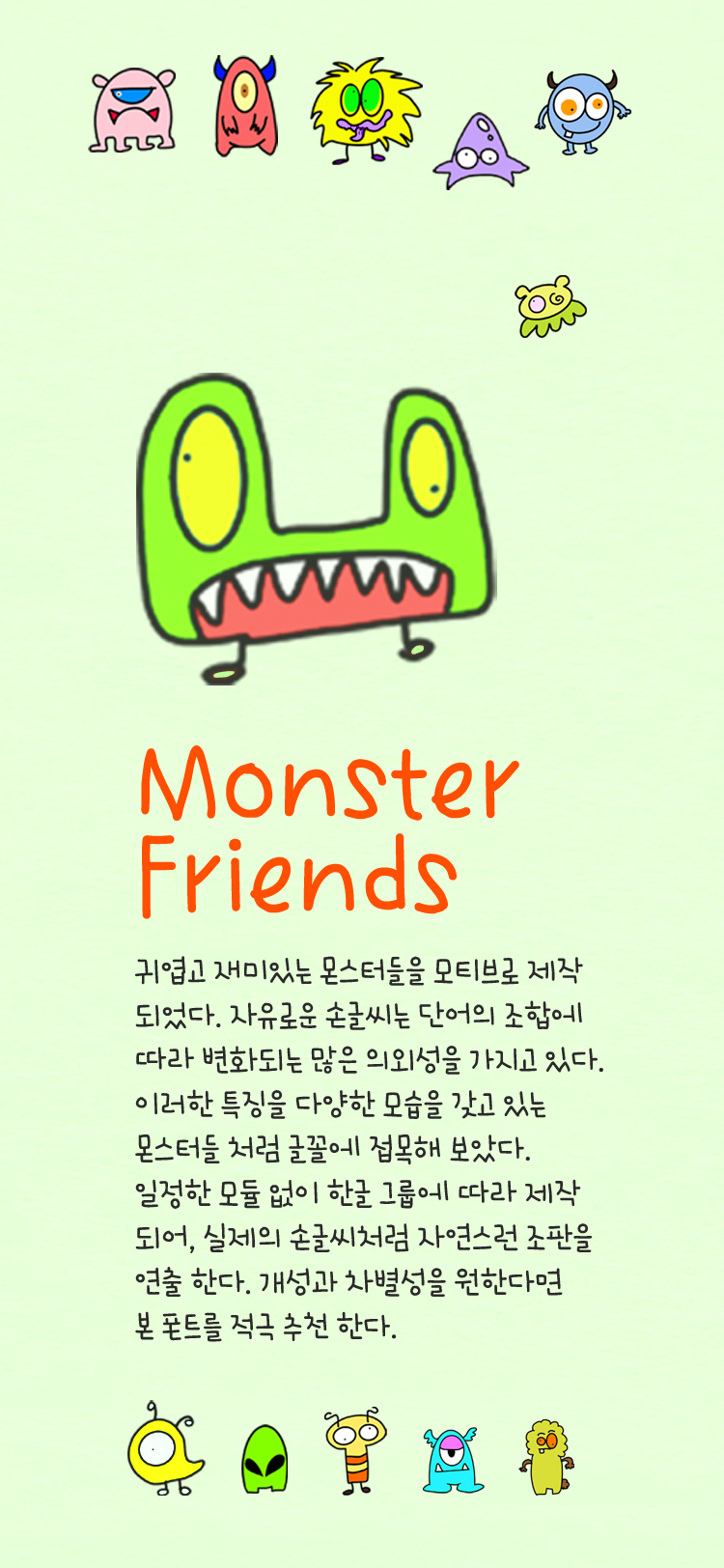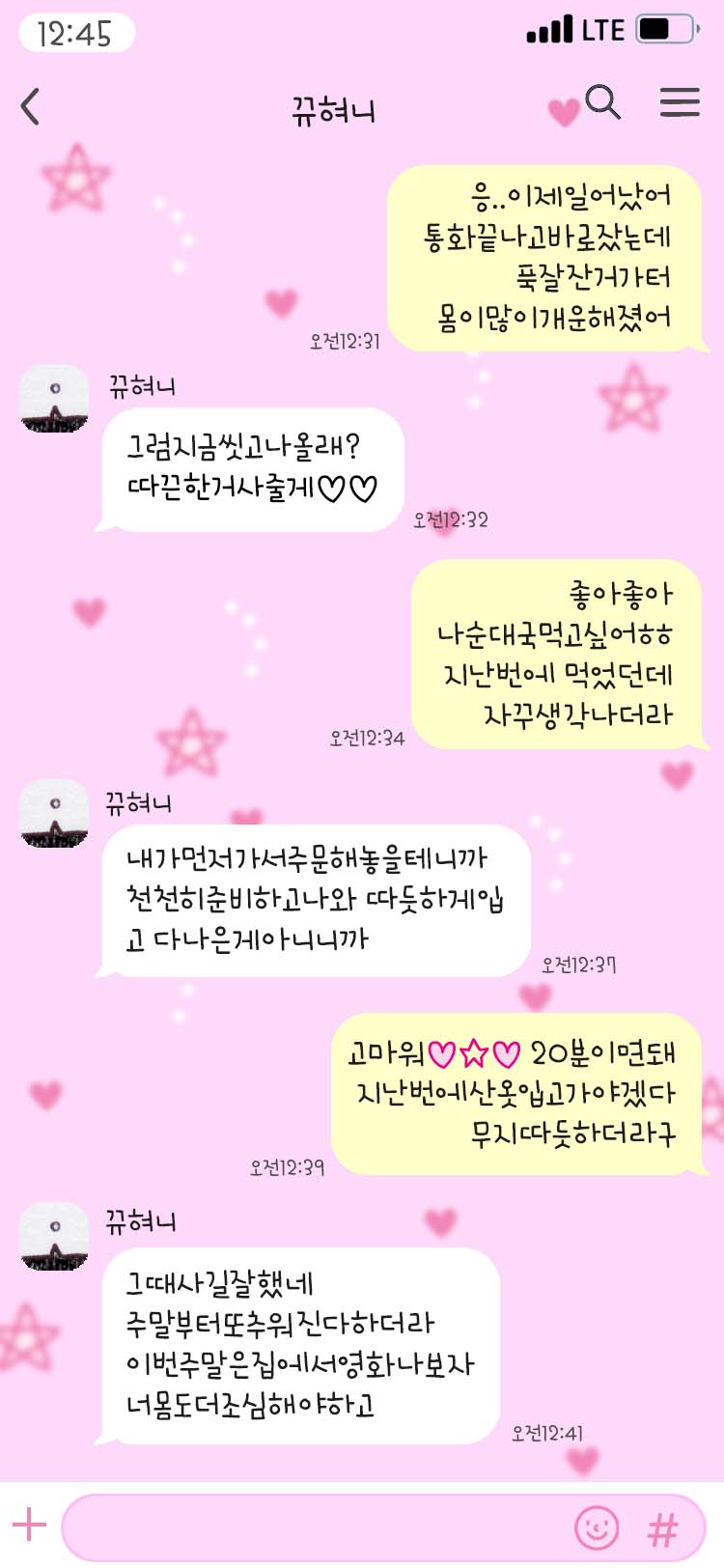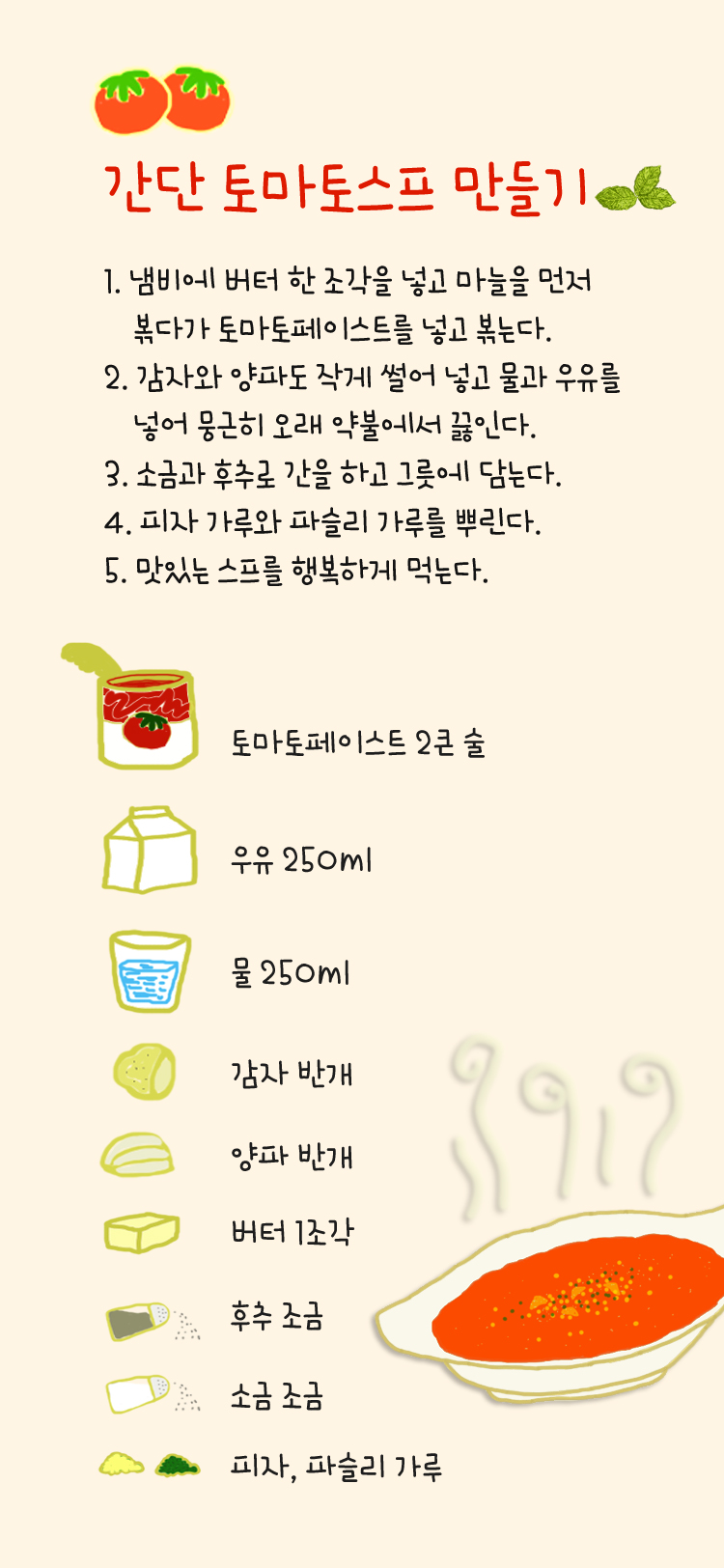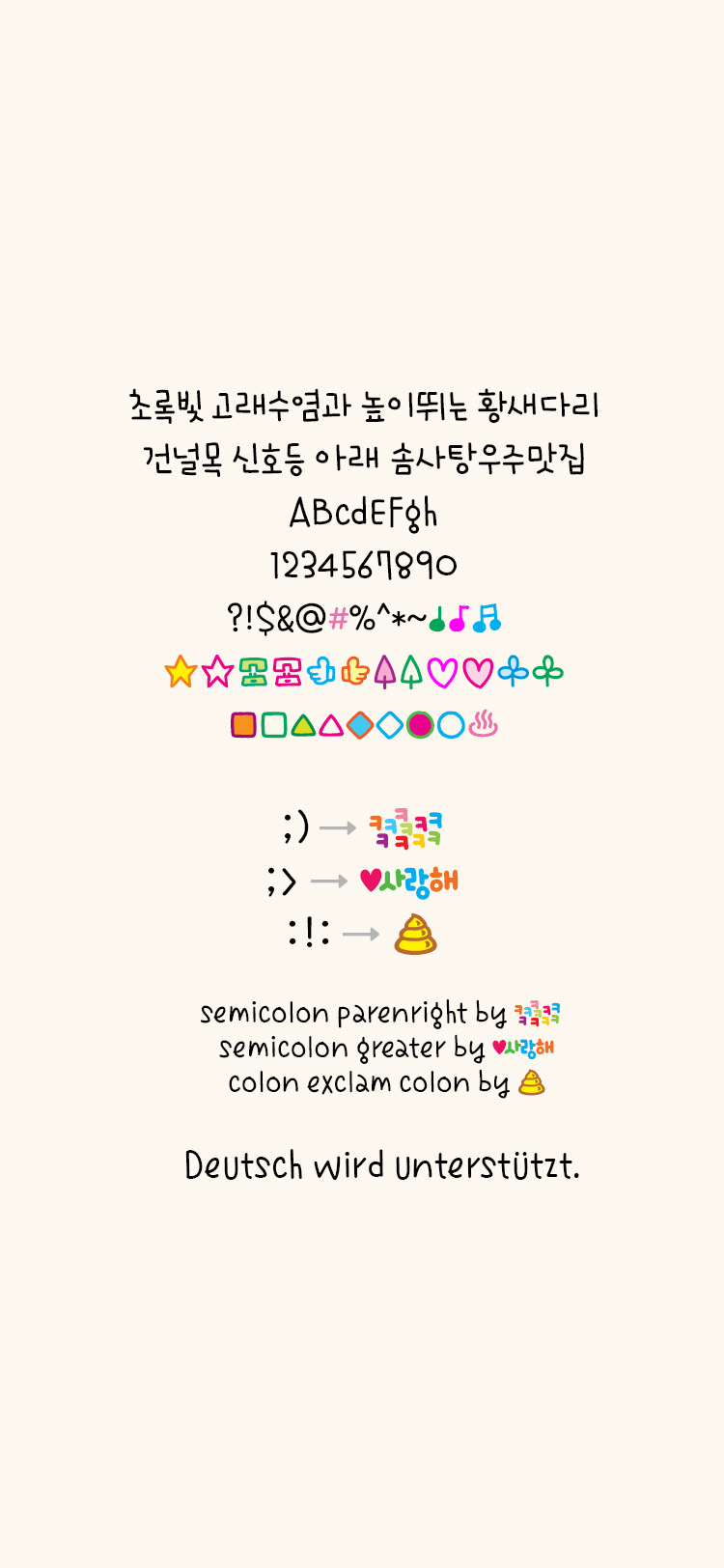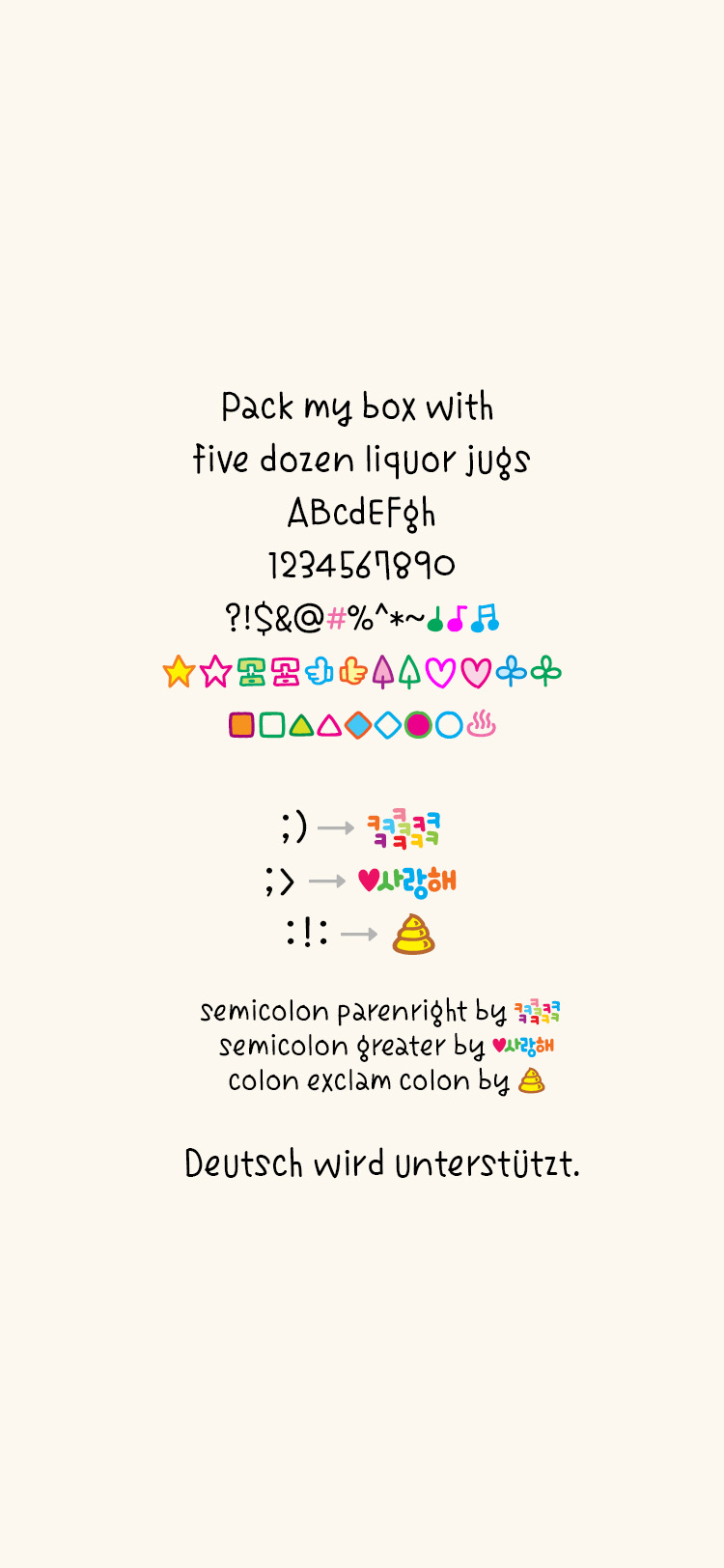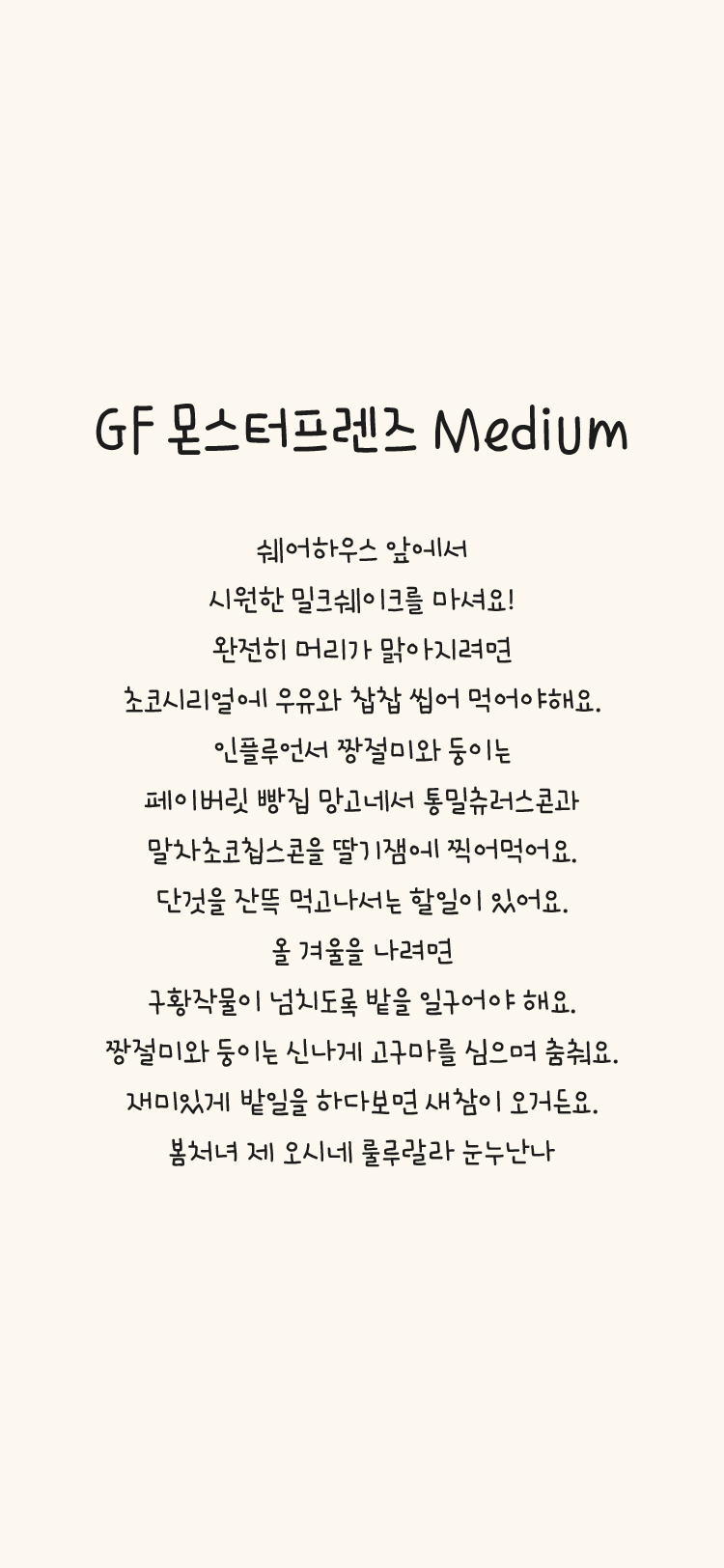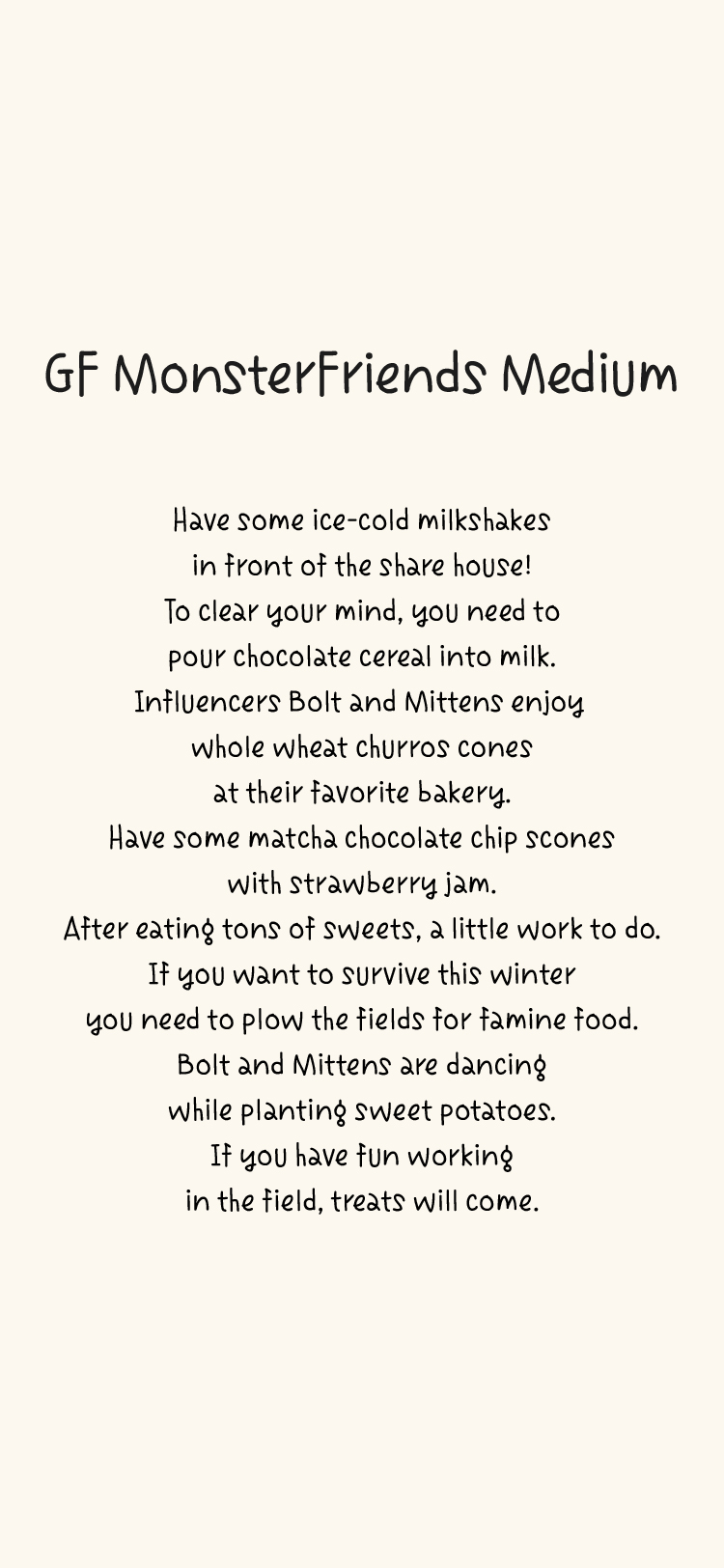
GF 몬스터프렌즈 M Medium
귀엽고 재미있는 몬스터들을 모티브로 제작 되었다. 자유로운 손글씨는 단어의 조합에 따라 변화되는 많은 의외성을 가지고 있다. 이러한 특징을 다양한 모습을 갖고 있는 몬스터들처럼 글꼴에 접목해 보았다. 일정한 모듈 없이 한글 그룹에 따라 제작 되어, 실제의 손글씨처럼 자연스런 조판을 연출 한다. 개성과 차별성을 원한다면 본 폰트를 적극 추천 한다.
semicolon parenright by ㅋㅋㅋ
semicolon greater by 사랑해
colon exclam colon by 황금똥